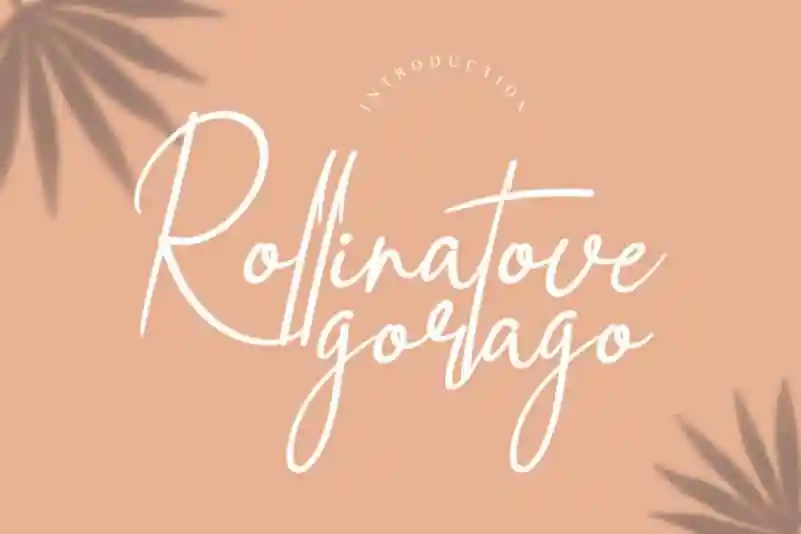
Rollinatove Handwritten Font – Fonte Grátis
Rollinatove Handwritten Font
A Rollinatove Handwritten Font é uma delicada e única tipografia escrita a mão. Ela oferece estilo elegante e eterno, perfeita para criar cartões de wedding incrivelmente belos, arte de carta surpreendentemente bonita, posts nas redes sociais impactantes e muito mais. A Rollinatove Handwritten Font é uma escolha ideal para aqueles que buscam um toque único em suas criações gráficas, capaz de dar um brilho especial ao seu design. Seja você designer gráfico ou aspirante a criador, a Rollinatove pode ajudar a transformar seus projetos em algo realmente especial e autêntico. Sua elegância distinta e sutilidade única fazem dela uma fonte perfeita para qualquer projeto que deseje destacar-se.